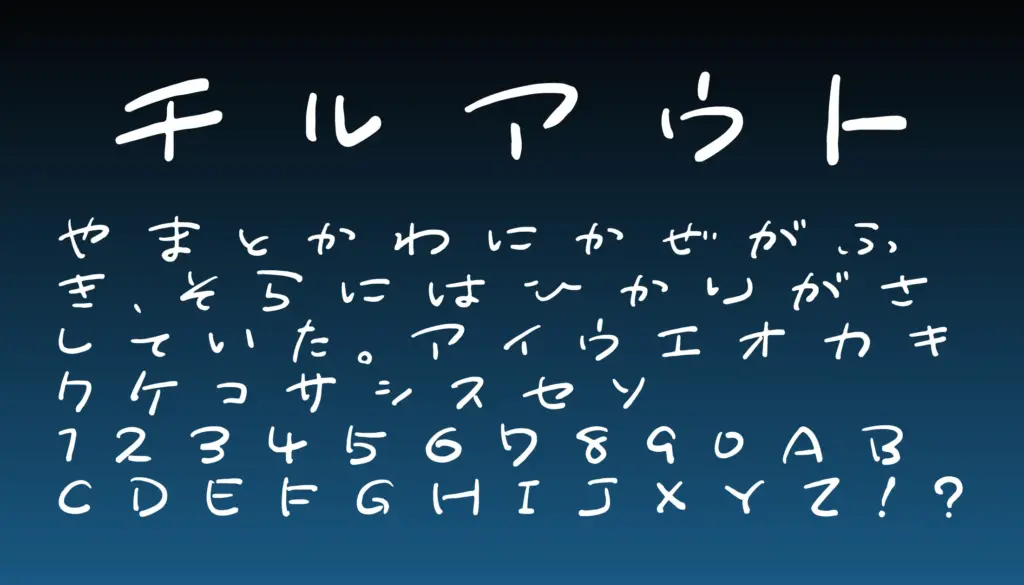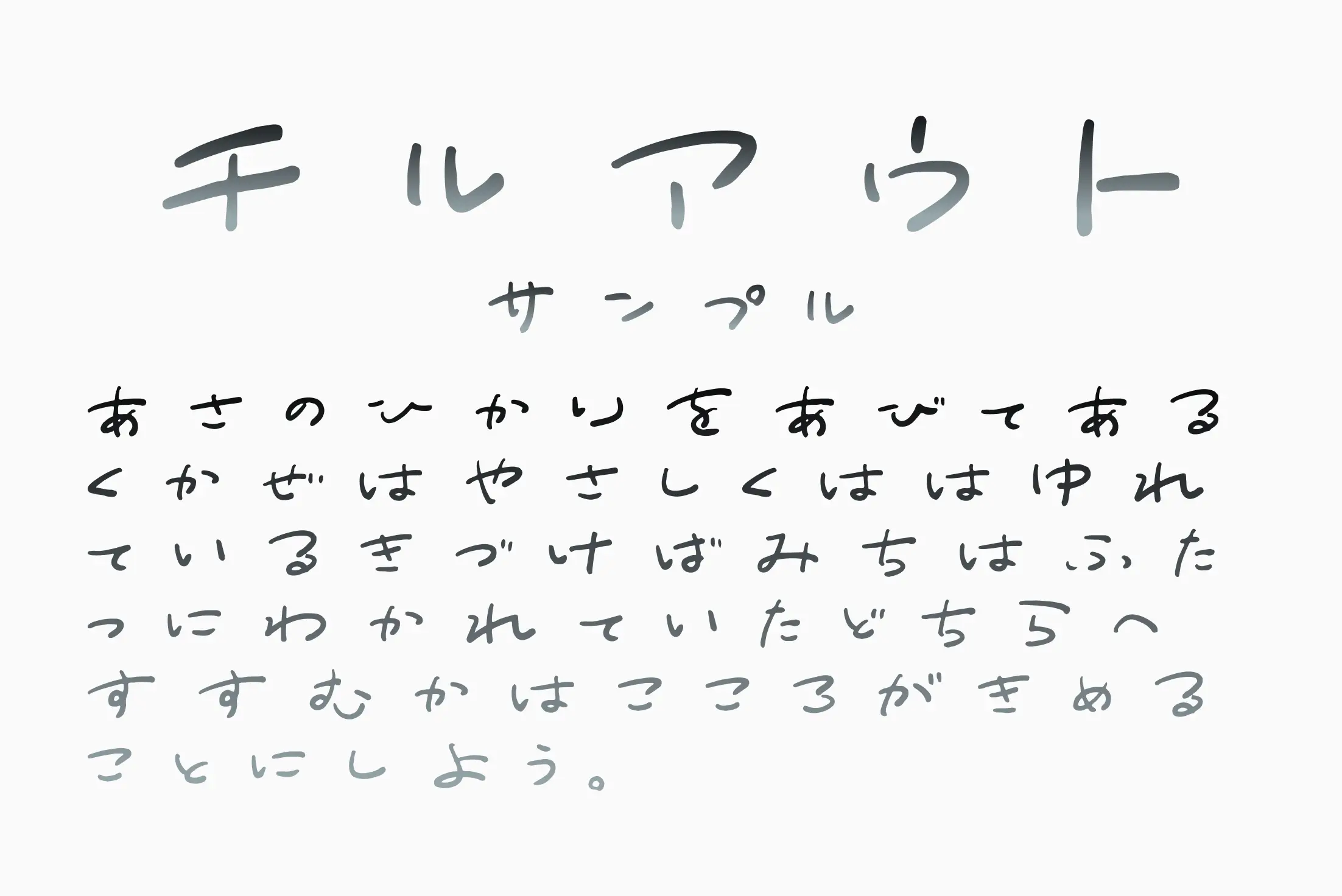
都会の夜景にも似合う、洗練されたナチュラルな手書きフォント。絶妙なリズムで揺れるラインが、やさしくも個性的な雰囲気を演出します。ひらがな・カタカナ・英数字に加え、記号も収録されており、タイトルロゴや動画テロップにも最適。さりげない抜け感が、大人っぽくチルな空気感を表現したい場面にぴったりの書体です。
チルアウト